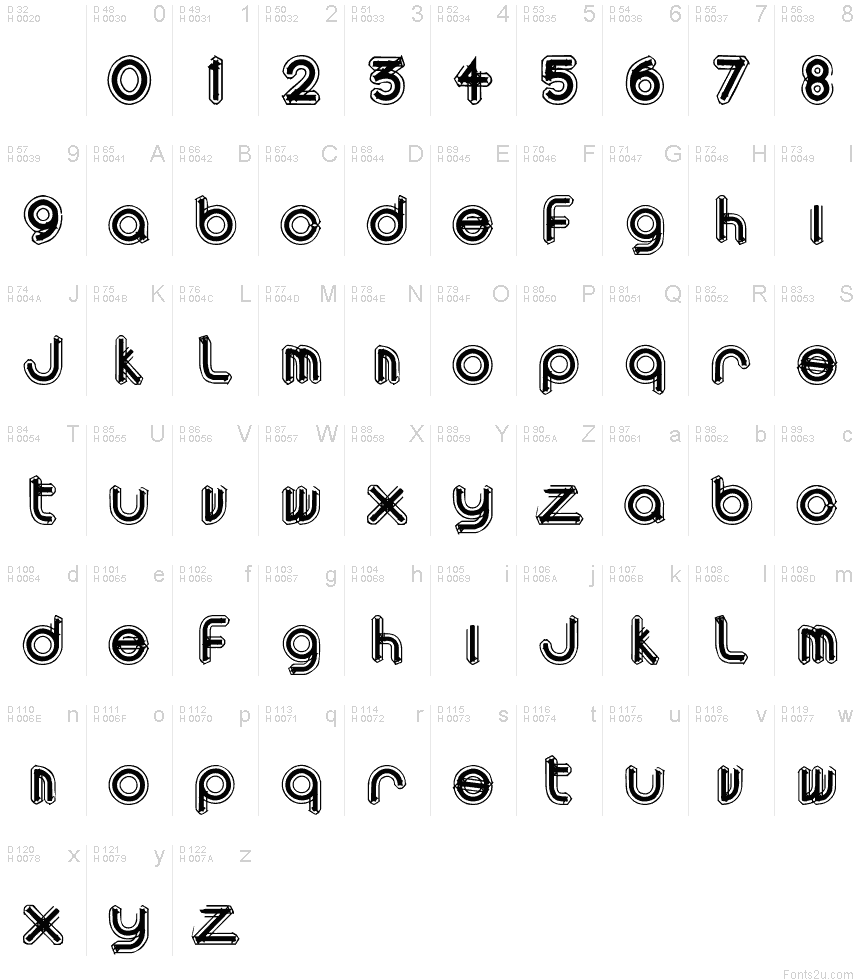
Area Outline هو خط عرض عصري ومجاني يتميز بتصميم خارجي يحوّل كل كلمة إلى مسار حلقي يشبه النيون. تقوم الخطوط السميكة والأنبوبية بتتبع كل حرف مرتين، مما يخلق تأثيراً متداخلاً يشبه المتاهة، ويبدو تقنياً ومرحاً في آنٍ واحد. تمنحه الأشكال الدائرية والمنحنيات الضيقة حضوراً جريئاً وحركياً، وكأن الخطوط في حالة حركة مستمرة.
باستخدام Area Outline، يصبح النص عنصراً رسومياً بحد ذاته، لذا فهو يتألق في الملصقات، وتصاميم فعاليات موسيقى EDM أو الألعاب، والعلامات التجارية المستقبلية، وأغلفة الألبومات، وإعلانات الويب، والبضائع ذات التصاميم البارزة. هذا الخط المجاني يبرز بوضوح في الأحجام الكبيرة، حيث يمكن للخطوط المتداخلة أن تأخذ مساحتها؛ قم بدمجه مع خط sans-serif هندسي نظيف من عائلة Area أو أي خط أساسي بسيط للحفاظ على وضوح التنسيق وقوته.